ジョジョといえば「ズキュウウゥン」や「メメタァ」などの特徴的な擬音と字体が魅力の一つですよね!
今回はデザインもフォントも詳しくない総務が「かわいすぎる」というだけで選んだ、個人的フリーフォントオブザイヤー受賞作をご紹介します。
このかわいさ!伝わりますでしょうか!イチオシのフリーフォントです。
コンセプトは「しろくまの肉球」をイメージしているとのことで、確かにこのぷっくり感…堪りません…。手書きフォントならではの、少しいびつなところもとても愛らしいです。
味のある筆書きフリーフォントです。この滲み具合、筆特有の掠れ、筆で書いたような味わい深さにぐっときます。丸っこい字体がまたかわいい!シンプルなデザインにそっと添えたくなるフォントです。
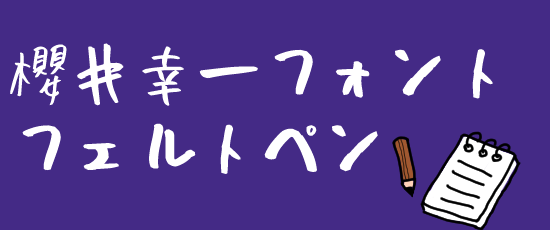
作者の櫻井幸一さんがフェルトペンで走り書きをしたフリーフォントです。
丸みをおびた字体と、細かったり太かったりと不均等な走り書きの雰囲気が、かわいいメーター振り切りそうなくらいかわいいです。手書きイラストとの相性が良さそうですね!
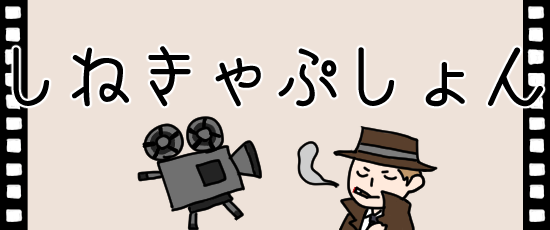
映画好きには堪らなく魅力的な、映画の字幕のようなフリーフォントです。
日本語・英字どちらにも対応しているので、ひたすら好きな台詞を打ち込むだけでも1日過ごせそうです。レトロな雰囲気がまたかわいい!様々なデザインで使えそうですね。
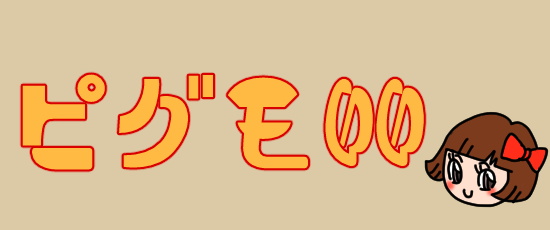
昭和広告のような、レトロな雰囲気の個性的なフリーフォントです。
かなり癖のあるフォントですが、その癖がクセになるかわいさです。日本語から英数字、記号にも対応しており、収録字数は約7000字!レトロなデザインにぴったりなフォントではないでしょうか。